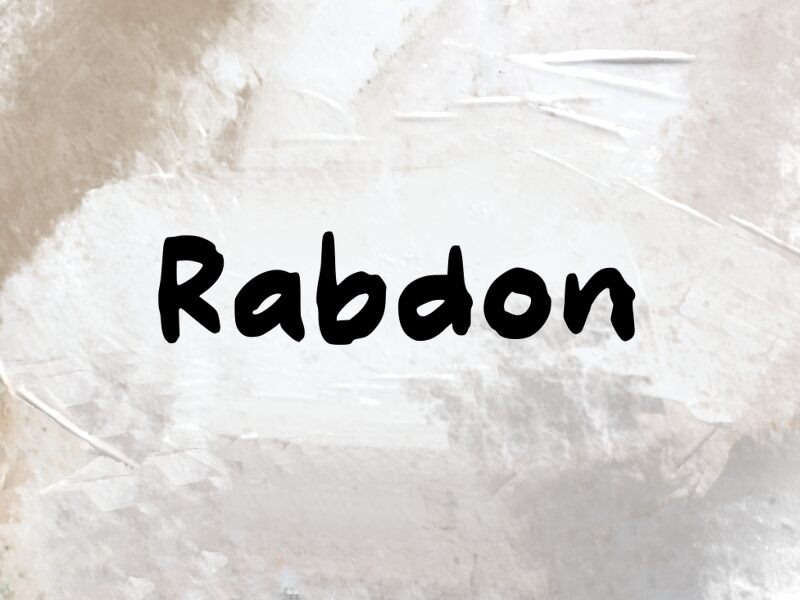
Rabdon от Wep — это бесплатный «жирный» шрифт, имитирующий письмо кистью, с легким, почти рукописным характером. Буквы выглядят широкими и слегка неровными, с мягкими скругленными краями и стремительными сужающимися штрихами, которые придают надписям живой, неформальный ритм.
Он идеально подходит для заголовков плакатов, повседневной упаковки, брендинга кофеен, графики для соцсетей и детских обложек — везде, где требуется дружелюбный, «живой» оттенок. Будучи бесплатным шрифтом, Rabdon лучше всего раскрывается в коротких акцидентных надписях, титрах и крупных выносках, где его массивные формы и игривая динамика сразу же привлекают внимание.
Rabdon
Презентация и наглядный образец шрифта Rabdon